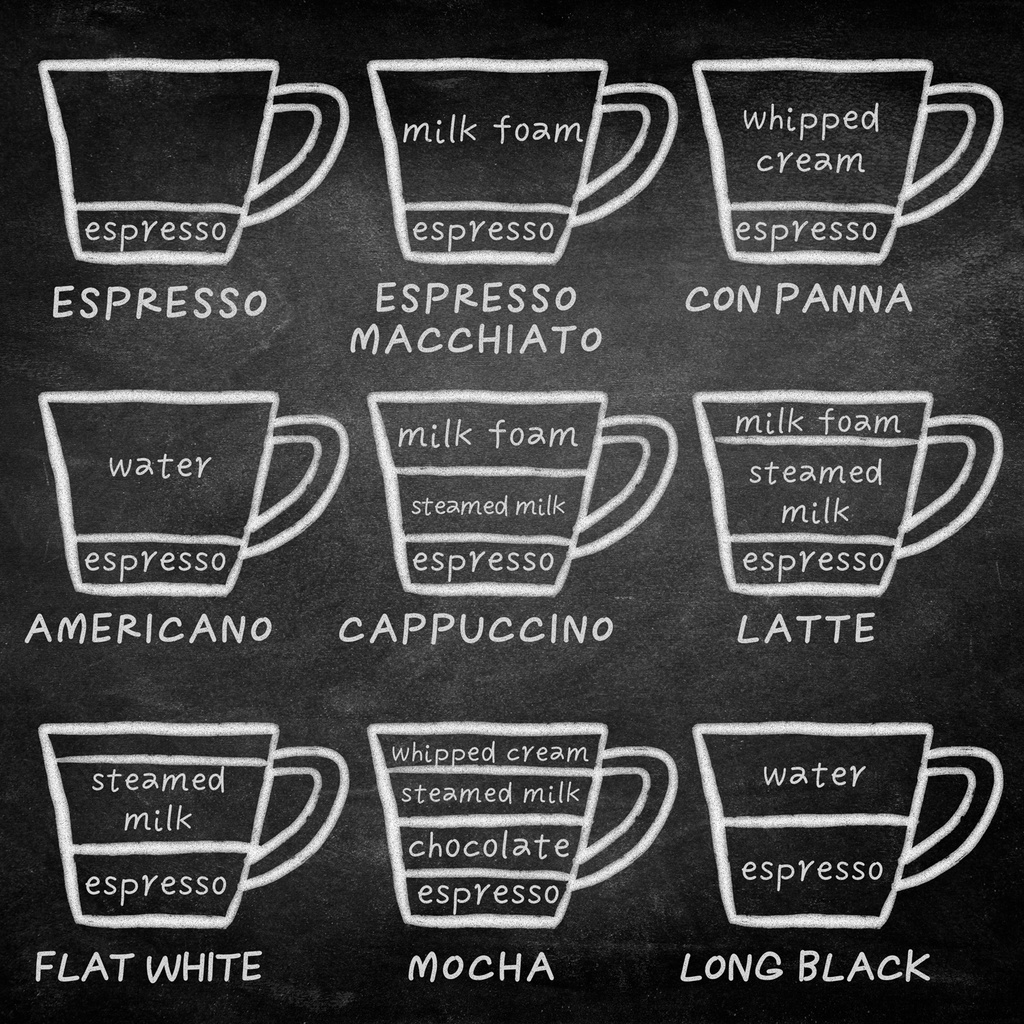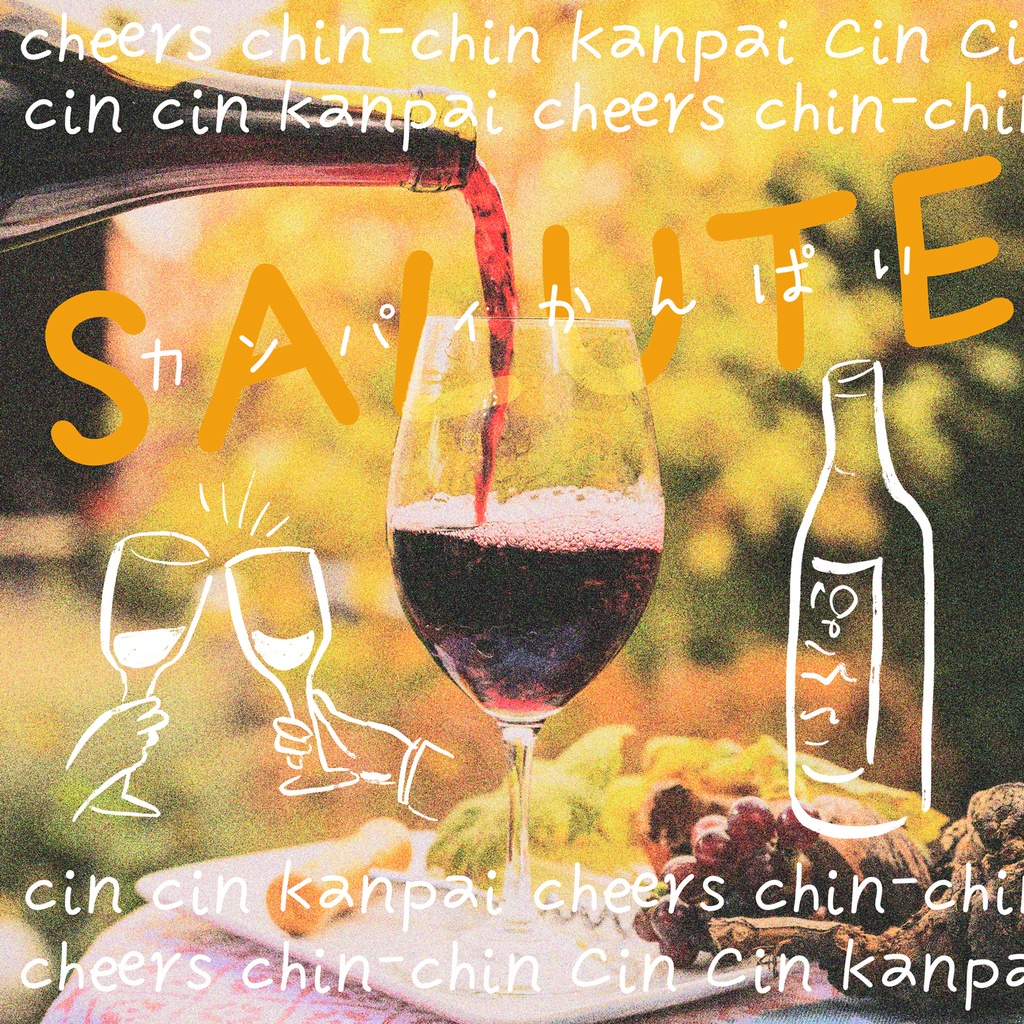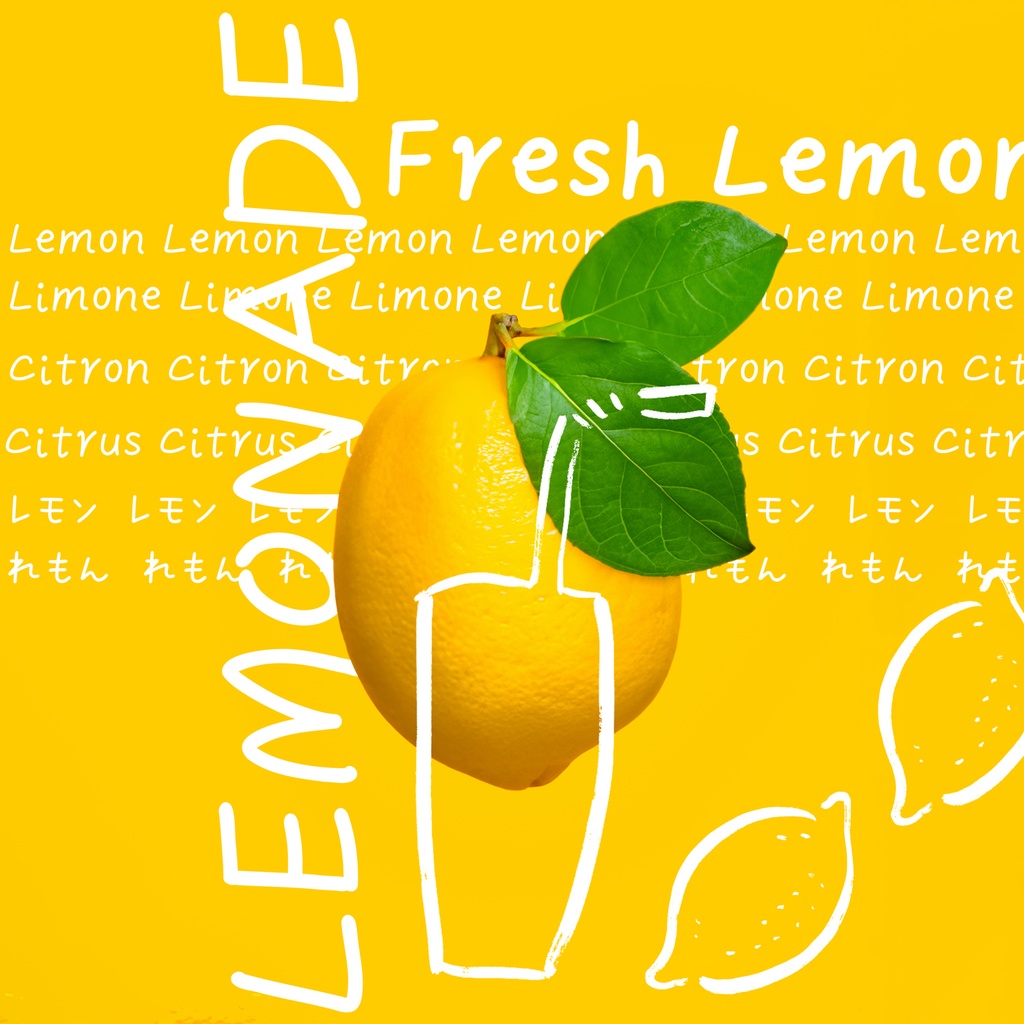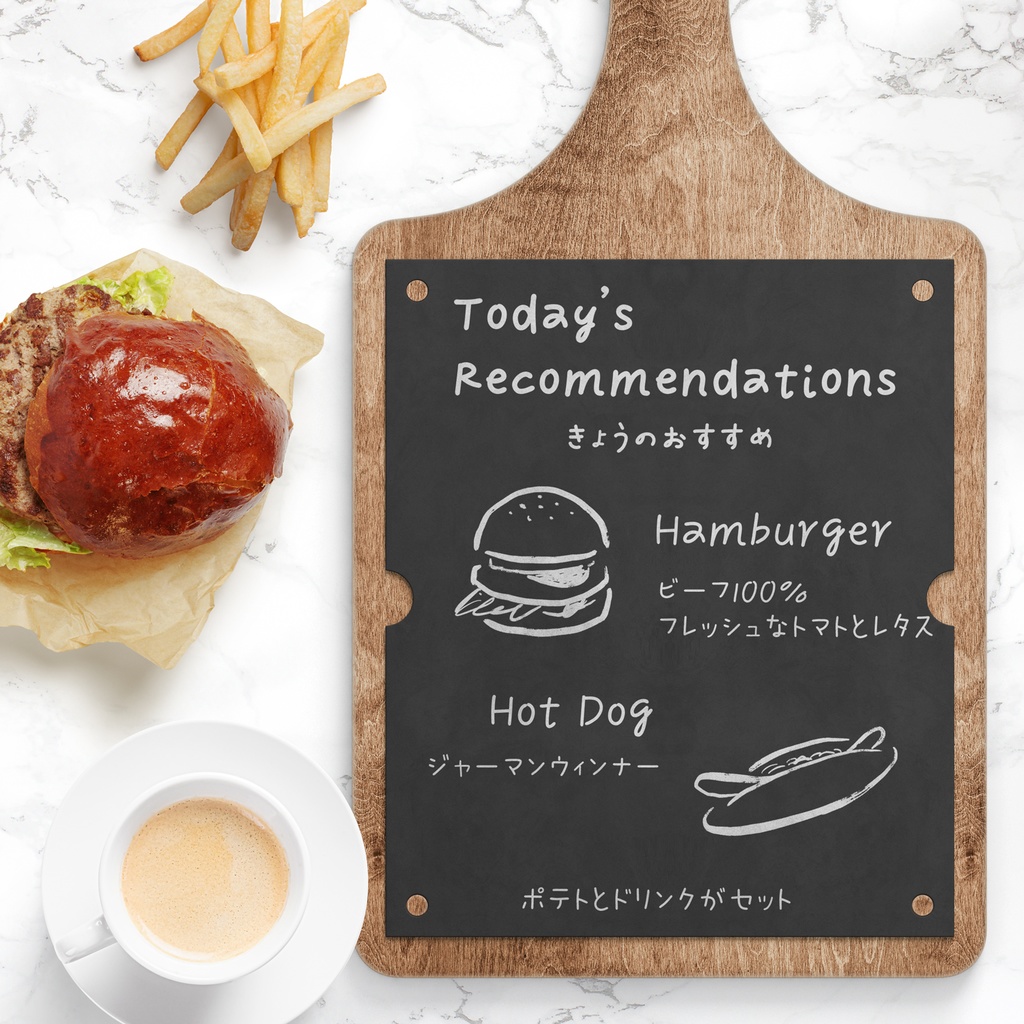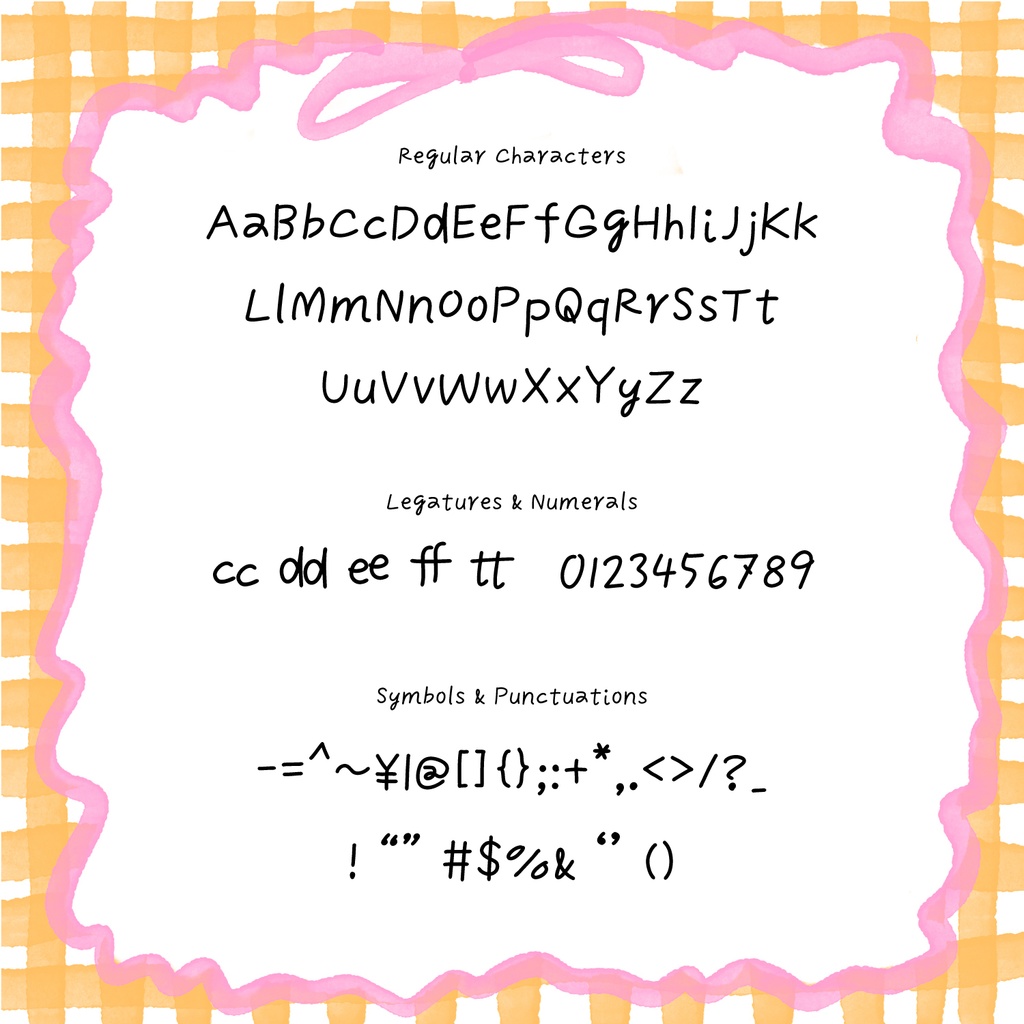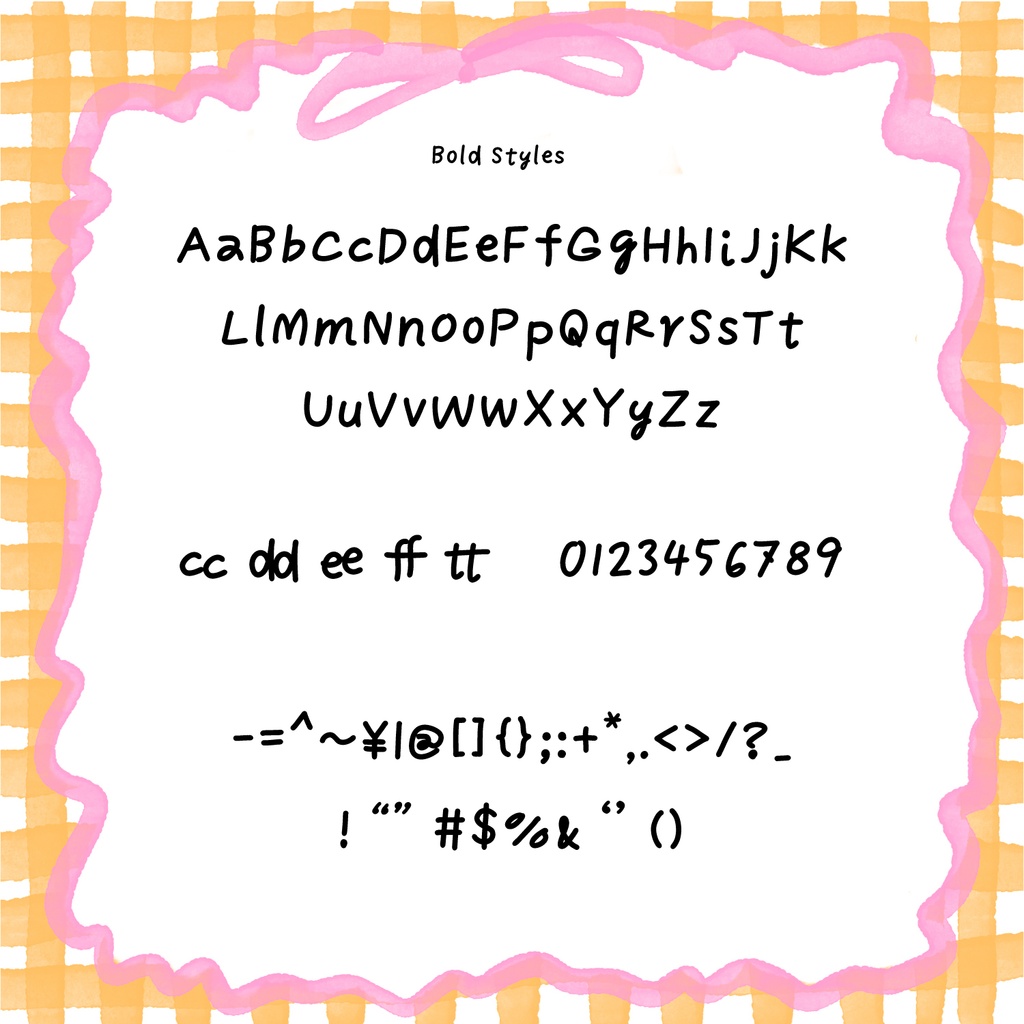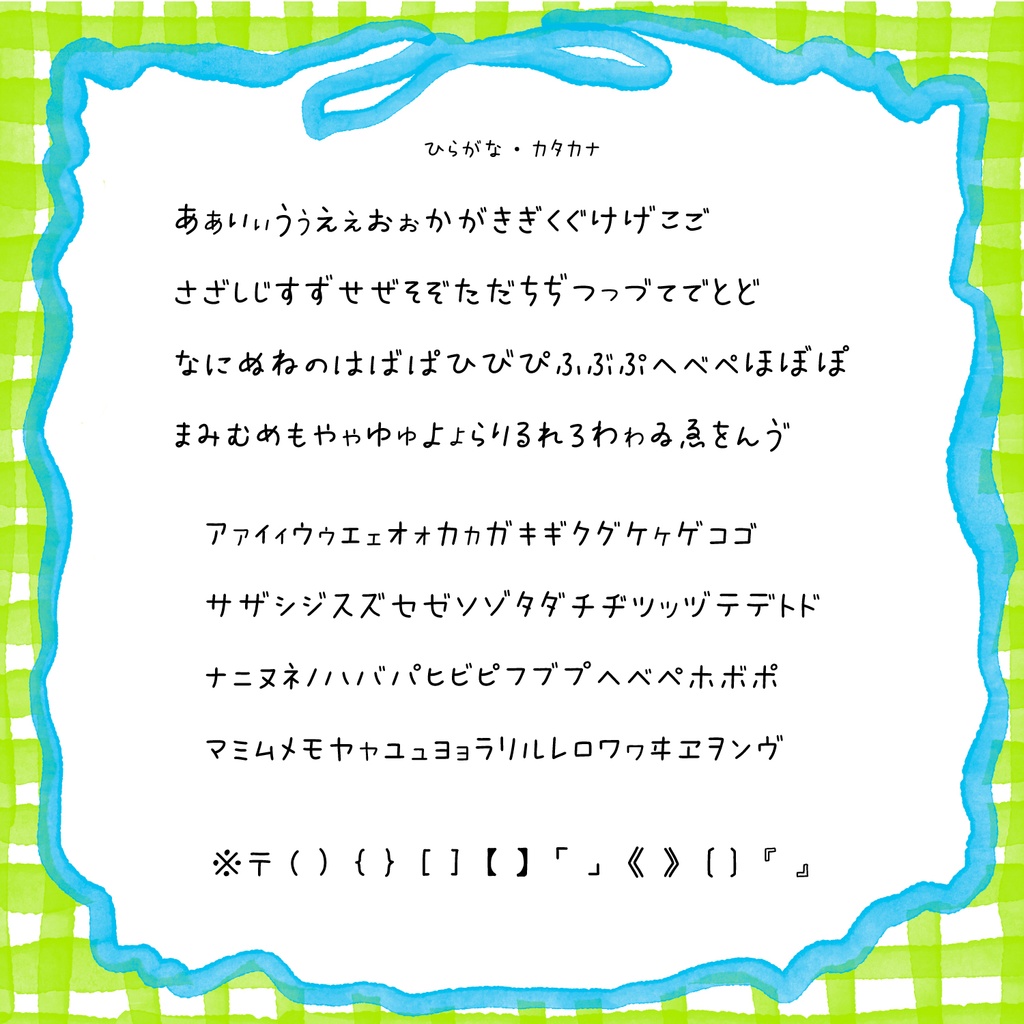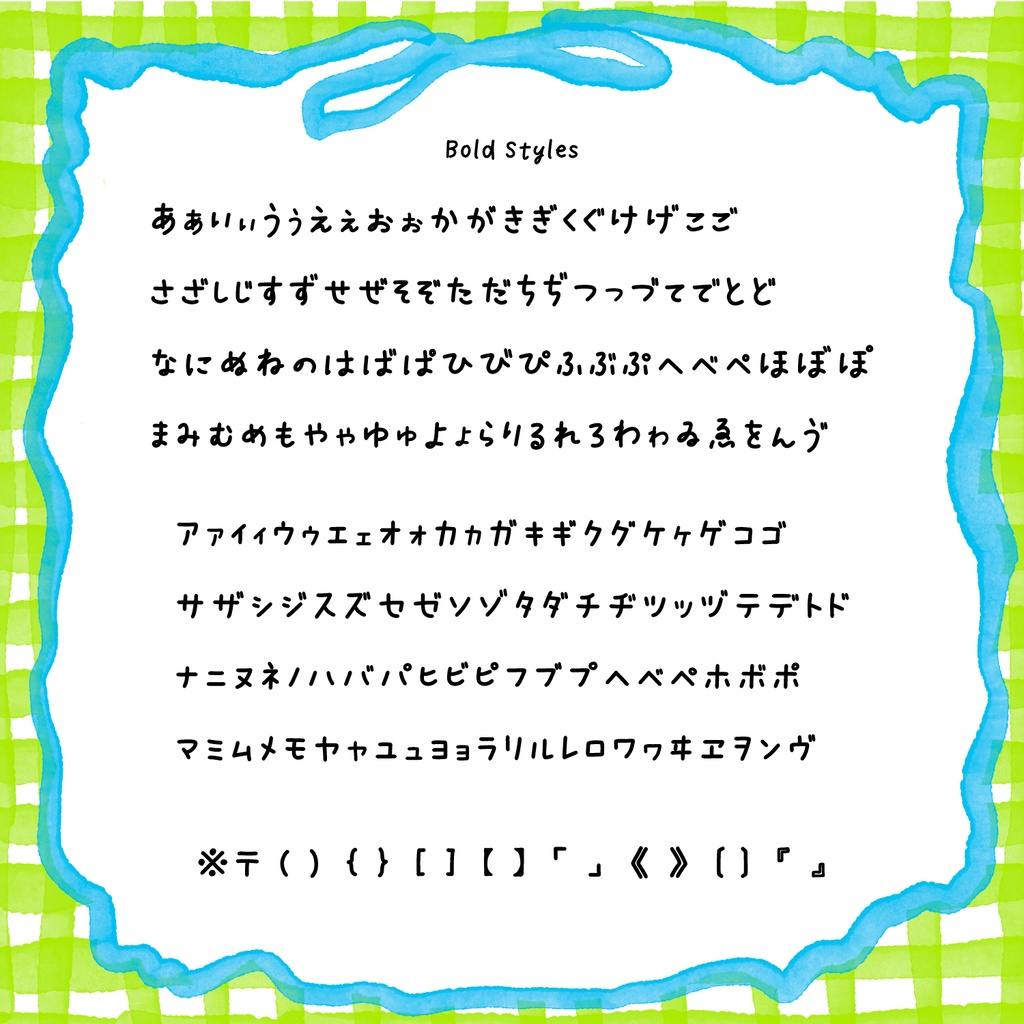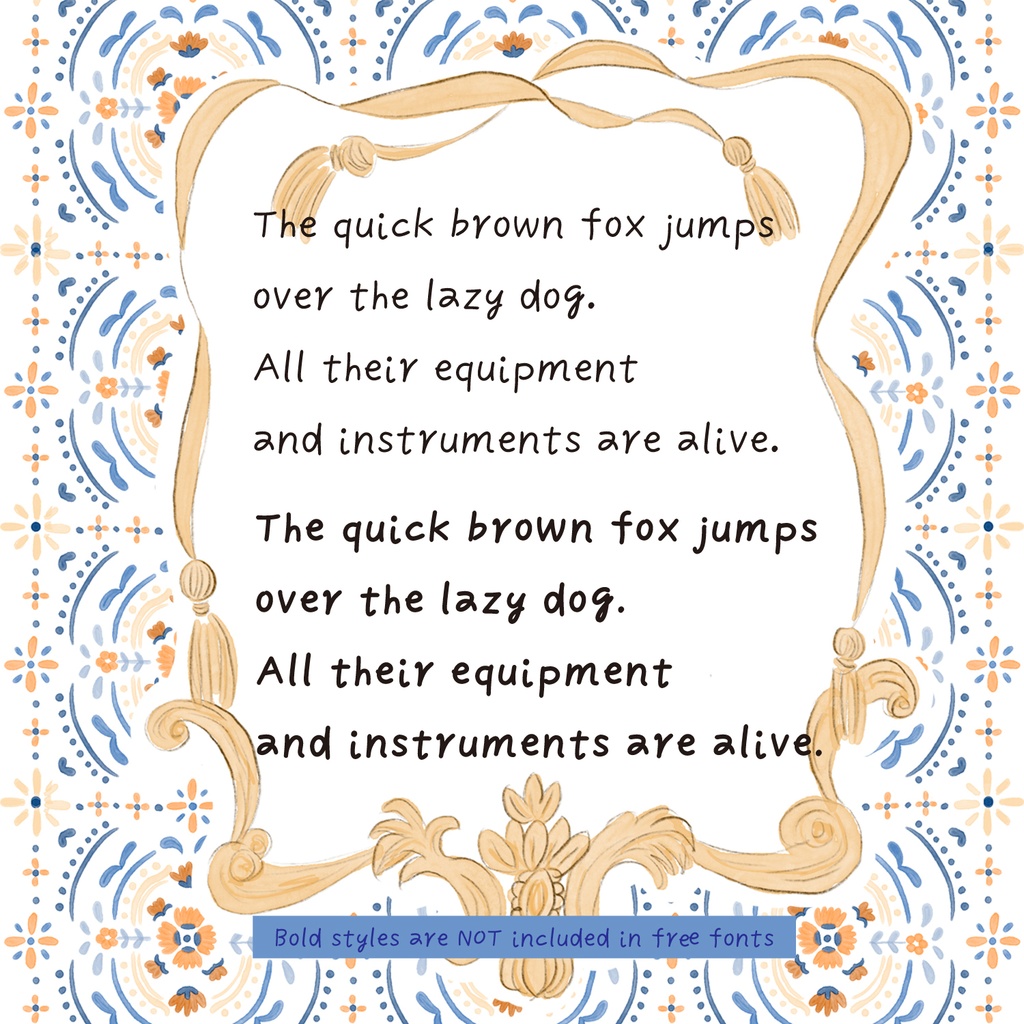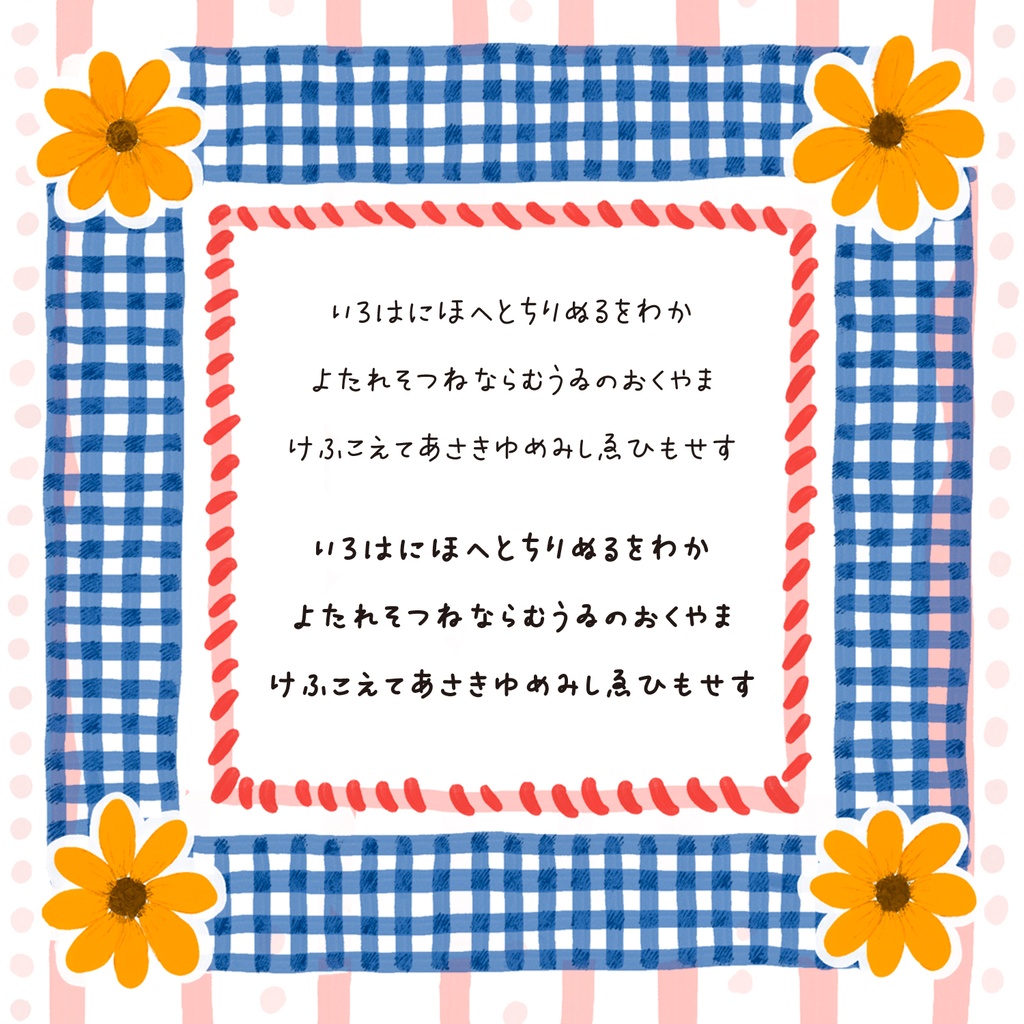
【商用可・縦書き対応】ゆる手書きフォント「カフェもじ」ー お試し無料フォントもあるよ
何気なく入ったのについつい長居してしまうほど、ものすごく居心地のよいカフェ。 店主さんのセンスが光る雑貨や小物がそっと並ぶギャラリーカフェ。 素材や味にこだわったメニューが味わえる自然派カフェ。 そんなカフェの空気感がただようフォントです。 メニューやポップに手書きしたようなゆるい文字をイメージしました。 ●「お試し版」FREE アルファベット・記号 収録 Regular(普通)のみ フォント形式:Open Type フォント 個人利用のみ可能です。 FOR Personal Use Only ●「ひらがな・カタカナ版」Regular(普通) ひらがな・カタカナ・アルファベット・記号 収録 フォント形式:OpenTypeフォント 縦書きできます。 商用利用OKです。 ●「ひらがな・カタカナ版」Bold(太字) ひらがな・カタカナ・アルファベット・記号 収録 フォント形式:OpenTypeフォント 縦書きできます。 商用利用OKです。 ●「ひらがな・カタカナ版」Family Set(Regular&Bold) ひらがな・カタカナ・アルファベット・記号 収録 フォント形式:OpenTypeフォント 縦書きできます。 商用利用OKです。 【動作環境】Windows / Mac 対応 【インストール方法】 Windows:ダウンロードしたZIPを解凍し、.otfファイルを右クリック→「インストール」 Mac:Font Bookにファイルをドラッグ&ドロップ 【ご利用条件について】 ・個人・商用利用ともにご利用可能です。 (フリーフォントは個人利用のみ) ・ご利用にあたってクレジット表記の必要はありません。 ・フォントの著作権は、放棄しておりません。 ・ご使用によるトラブルや損害等、一切の責任を負いませんのでご了承ください。 下記の事項でご利用いただけます。 1. WEB・印刷物・動画へのデザインに使用 2. ソーシャルメディア、電子書籍への使用 3. ロゴへの使用(商標登録は不可) (※ご不明な場合は、お問い合わせください。) 4.LINEスタンプへの使用 ※イラスト等のセリフへの使用可能 フォントがメインキャラクターにならない場合のみ使用可能です。 下記の事項でのご利用は不可とさせていただきます。 1. フォントデータの販売 2. フォントデータの再配布 3. 商標登録 4. 公序良俗に反するものへの利用